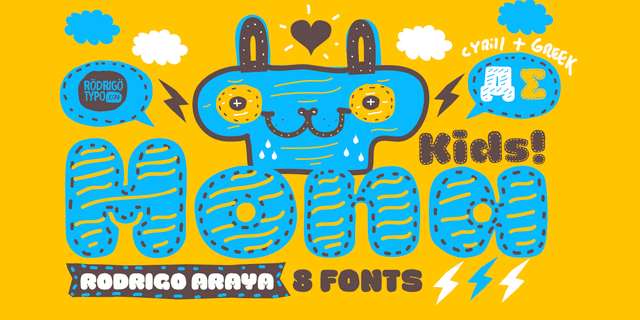
Шрифт Mona Kids – самый игривый, улыбчивый и наивный шрифт в мире. Его легко перепутать с пончиком и сьесть. В этой корзине пирожных более 550 глифов! Шрифт разработан в 2016 году Родриго Арая Салас.
Ассоциации c начертанием La Mona Kids BaseКачества и характер:
веселый, пузатый, задорный, смешной, дружелюбный, добродушный, добрый, радостный, игривый, приветливый, озорной, оригинальный, свежий, спелый, сочный, вкусный, тяжелый, заметный, броский, детский, наивный, карикатурный, милый, мультяшный, яркий, остроумный, домашний, летний, мягкий, щедрый, пышный, уютный, приятный, живой, доброжелательный, гладкий, праздничный, тесный, толстый, прикольный, няшный, улыбчивый, аппетитный, сладкий, счастливый, зимний, снежный, творческий, фруктовый, ягодный, обильный, изобильный, насыщенный, пухлый
молоко, булочка, десерт, сладости, кондитерская, выпечка, булочная, мягкая игрушка, детская книжка, краски, краска, юмор, анимация, игрушка, детское питание, еда, закуска, зоопарк, клоун, раскраска, игра, фаст фуд, пончик, зоомагазин, животные, отдых, цирк, мультфильм, детский сад, утренник, сок, каникулы, торт, конфеты, крем, сгущенка, варенье, подарки, праздник, день рождения, шоу, телевидение, соус, сметана, кетчуп, жвачка, подгузник, чипсы, котики, наклейка, стикер, фрукты, мармелад, развлечения, зима, сыр Стилистика: